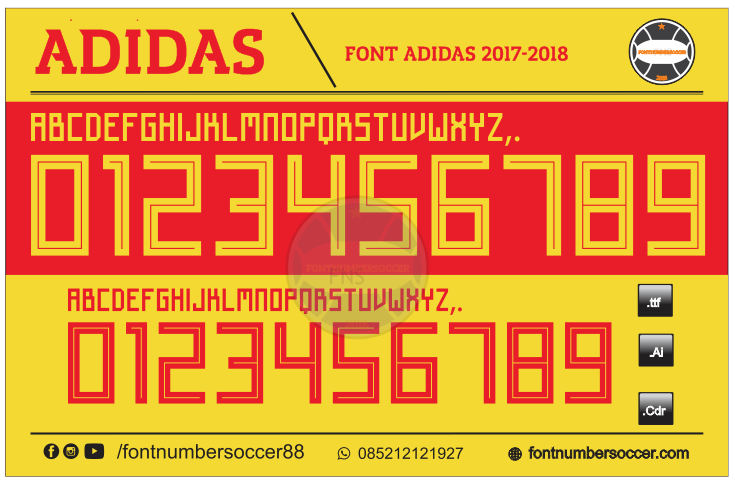
Font Adidas 2017-2018 | World Cup 2018 (Update)
Font Adidas 2017-2018
Pada kesempatan hari ini saya akan menshare salah satu font paling terkenal yaitu font adidas 2017-2018. Semua tim nasional yang disponsori oleh Adidas akan menggunakan font ini pada piala dunia di Rusia. Team nasional yang menggunkan font adidas antara lain Rusia, Spanyol, Jerman, Argentina, dan beberapa tim lainnya. Kredit masuk ke pembuat asli dan fontnumbersoccer.com.